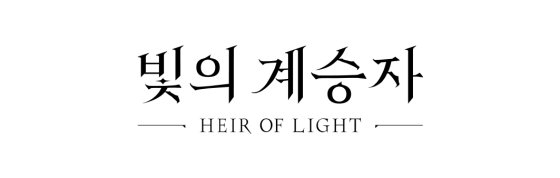
빛의 계승자 폰트
빛의 계승자 폰트. 사용범위 프리 개인 기업 국가 국내 국외 빛의계승자체 라이센스 빛의계승자체 의 지적재산권은 펀플로와 산돌 커뮤니케이션즈에 있습니다. 빛의 계승자체안녕하세요 머치퍼니 입니다. 12 26 게임빌에서 이번에 출시하는 모바일게임 빛의계승자 에서 사용한 폰트를 무료로 배포한다고 발표했다. 태그 빛의계승자.
일명 계승자체 라고 불리는 이 서체는 새벽별 교단에서 사용하는 공식 서체이다. The font is based on a book passed down by morning star the head of the church and the savior of mankind in order to protect humanity from the dark blood. 페이스북 source 폰트 카테고리의 다른 글. 상업적 용도나 재배포는 당연히 금지 게임빌 허가 받아야한다.
한글 빛의 계승자체 상업용 무료폰트 바로 다운로드. 오늘은 빛의 계승자 게임빌에서 무료로 배포해준 폰트를 소개. 빛의계승자체 는 개인 및 기업 사용자를 포함한 모든 사용자에게 무료로 제공되며 상업적 목적으로도 사용하실 수 있습니다. 펀플로 빛의 계승사자체 를 소개합니다.